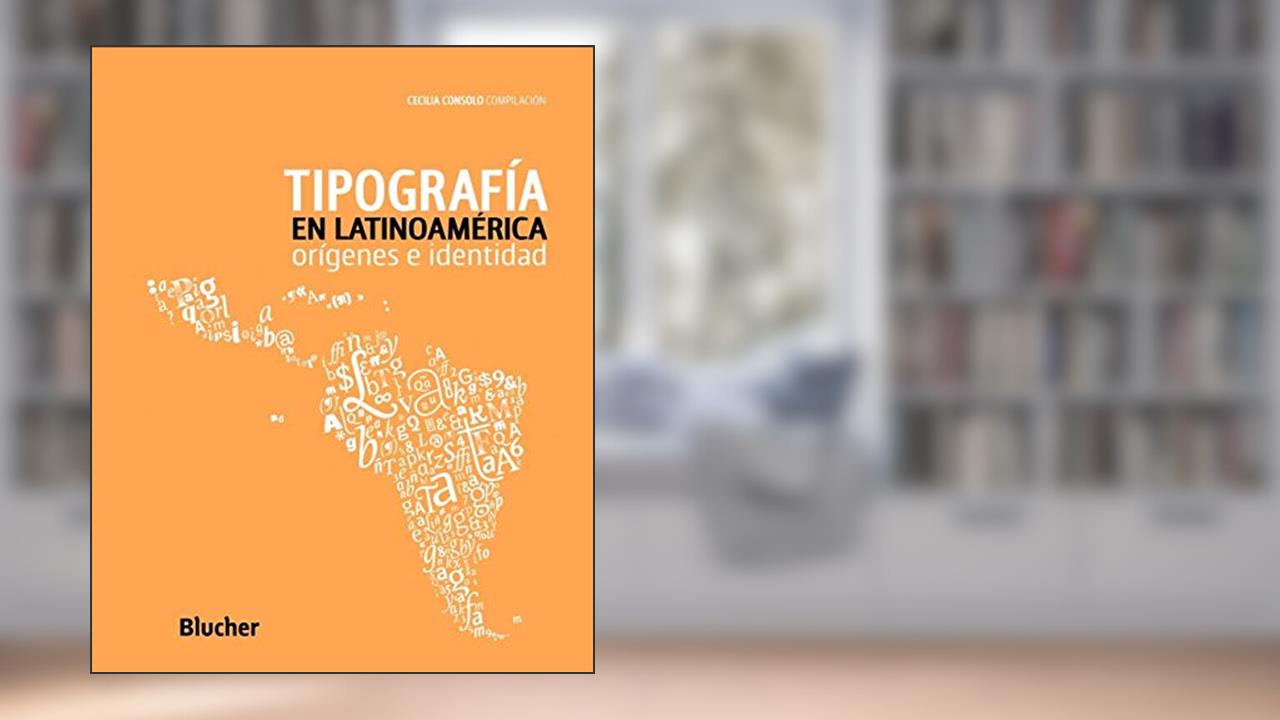
A tipografia transcende a mera disposição de letras; ela é a alma visual de uma cultura. Ao abrir as páginas de Tipografía en Latinoamérica: Orígenes e Identidad, você se depara com um mergulho profundo e fascinante nas raízes e na evolução desse universo no contexto latino-americano. Um convite irresistível para explorar como os símbolos impressos moldaram, e continuam a moldar, identidades e narrativas em um continente tão rico e diverso.
Os autores Alejandro lo Celso, Marina Garone Gravier e Rubén Fontana embarcam em uma jornada de descobertas que vai além da estética, explorando a história, a política e as influências sociais que moldaram a tipografia na América Latina. Essa obra é um baluarte que desafia a superficialidade, obrigando você a refletir sobre como a forma das letras pode carregar sentimentos, ideologias e a essência de um povo.
Ao longo das 160 páginas, o leitor é levado a participar de uma conversa vibrante sobre a identidade latino-americana. A obra traça uma linha do tempo impressionante que ilustra como os primeiros impressos chegaram ao continente e como cada tipografia, cada fonte, cada estilo reflete um pedaço da cultura imediatamente reconhecido. O que pode parecer simples aos olhos desavisados, revela-se, na verdade, como um campo de batalha estética onde tradições indígenas, influências coloniais e inovações contemporâneas se entrelaçam para criar um mosaico inigualável.
Ao explorar a tipografia, os autores não apenas documentam, mas também celebram a transição e a resistência cultural, mostrando como a tipografia é um reflexo da luta por representação e identidade. Eles nos obrigam a encarar a verdade: a tipografia não é apenas um conjunto de letras; é um veículo de comunicação que carrega o peso da história e da cultura.
Em tempos onde a identidade se torna ainda mais fragmentada e a globalização ameaça as particularidades locais, Tipografía en Latinoamérica se destaca como um grito necessário. Ao final da leitura, você não apenas conhecerá mais sobre a evolução tipográfica, mas também sobre a essência cultural que ela representa. Prepare-se para uma transformação mental que pode mudar a forma como você olha para o mundo - e para a próxima letra que você encontrar por aí.